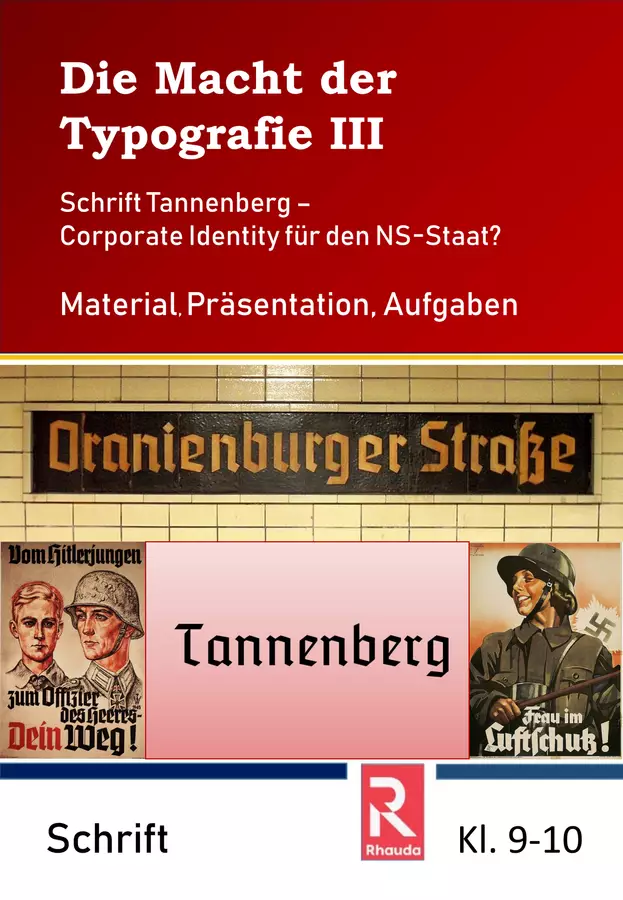
Du möchtest mit Deinen Lernenden die spannende Welt der Typografie entdecken und verstehen, wie Schriften politische Botschaften transportieren können? Dieses Material hilft Dir dabei, genau diese Fragen zu beleuchten und eine kritische Auseinandersetzung anzuregen.
• einen direkten Vergleich von Schriftarten wie Tannenberg, Fraktur und Antiqua ermöglicht.
• die historische Rolle von Schriften im Nationalsozialismus beleuchtet und erklärt, warum bestimmte Typen bevorzugt wurden.
• zur kritischen Diskussion anregt, ob Schriften neutral sein können und welche kulturellen sowie politischen Bedeutungen sie tragen.
• praktische Einblicke gibt, wie Typografie politische Botschaften verstärkt und wie man Schriften mit historischer Relevanz verantwortungsvoll einsetzt.
• authentische Beispiele und vielfältiges Bildmaterial aus der Zeit des Nationalsozialismus für eine lebendige Unterrichtsgestaltung bietet.
• Typografische Merkmale erkennen: Sie lernen, die charakteristischen Eigenschaften verschiedener Schriftarten zu identifizieren und zu benennen.
• Historische Kontexte verstehen: Sie entwickeln ein Bewusstsein dafür, wie Schriften in historischen und politischen Kontexten eingesetzt wurden und welche Rolle sie dabei spielten.
• Kritische Medienkompetenz aufbauen: Sie üben sich darin, die Wirkung von Typografie in Medien kritisch zu hinterfragen und zu analysieren.
• Verantwortungsvollen Umgang reflektieren: Sie diskutieren den ethischen Umgang mit Schriften, die eine politische Vergangenheit haben, und entwickeln ein fundiertes Kontextbewusstsein.
• Argumentationsfähigkeit stärken: Sie formulieren eigene Standpunkte zu komplexen Fragen der Schriftverwendung und begründen diese überzeugend.
Die Macht der Typografie III - Tannenberg - Corporate Identity für den NS-Staat?
Dieses Materialpaket betrachtet weniger die technischen Feinheiten und Fachterminologie von Schrift, sondern beleuchtet deren Wirkung und Anwendungsbereiche. Schüler/innen reflektieren ihre Wahrnehmung von Schrift, lernen verschiedene Schriftarten und deren Wirkung und Einsatz kennen und wenden verschiedene Schriftarten reflektiert an. Im Fachübergriff mit Geschichte betrachten die Schüler/innen die Wirkung von gebrochenen Schriften, lernen am Beispiel der Schrift "Tannenberg" deren Anwendung während der NS-Zeit kennen und diskutieren anschließend, ob Schriften neutral sein können.